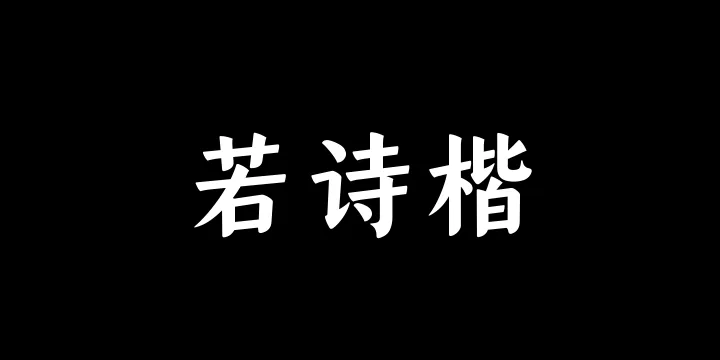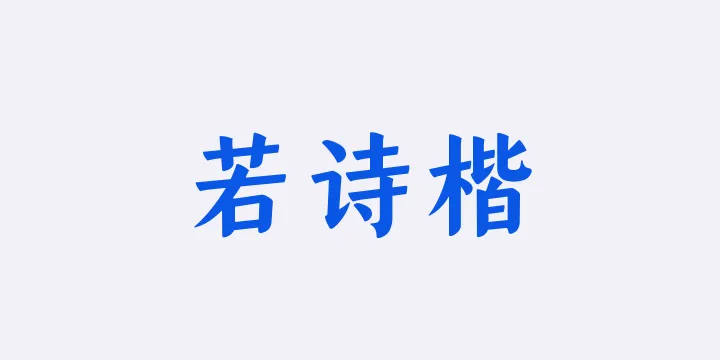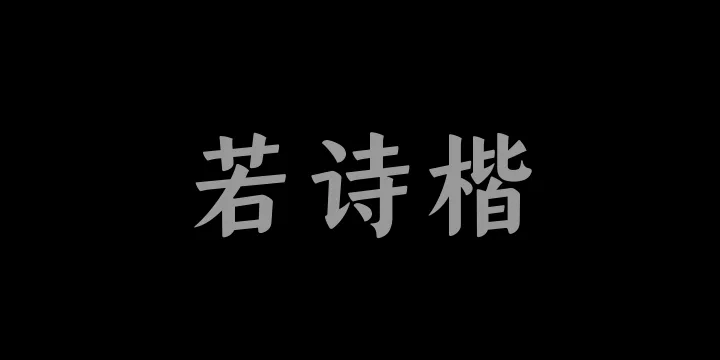
山海若诗楷75W By 山海字库 商用字体
字体全名: 山海若诗楷75W
字体简介: 山海若诗楷75W,是一款全新的楷体字体,是山海若诗楷字体家族系列中的细款,编号75W,包含汉字9169个,符号200+个。该字体字形优美文雅,诗意内敛,取楷体细腻的书写笔画,书法的运笔走势蕴含其中,流畅自然,蕴含东方审美韵味,尽显优雅从容,秀雅清新。
所属分类: 楷书手写体